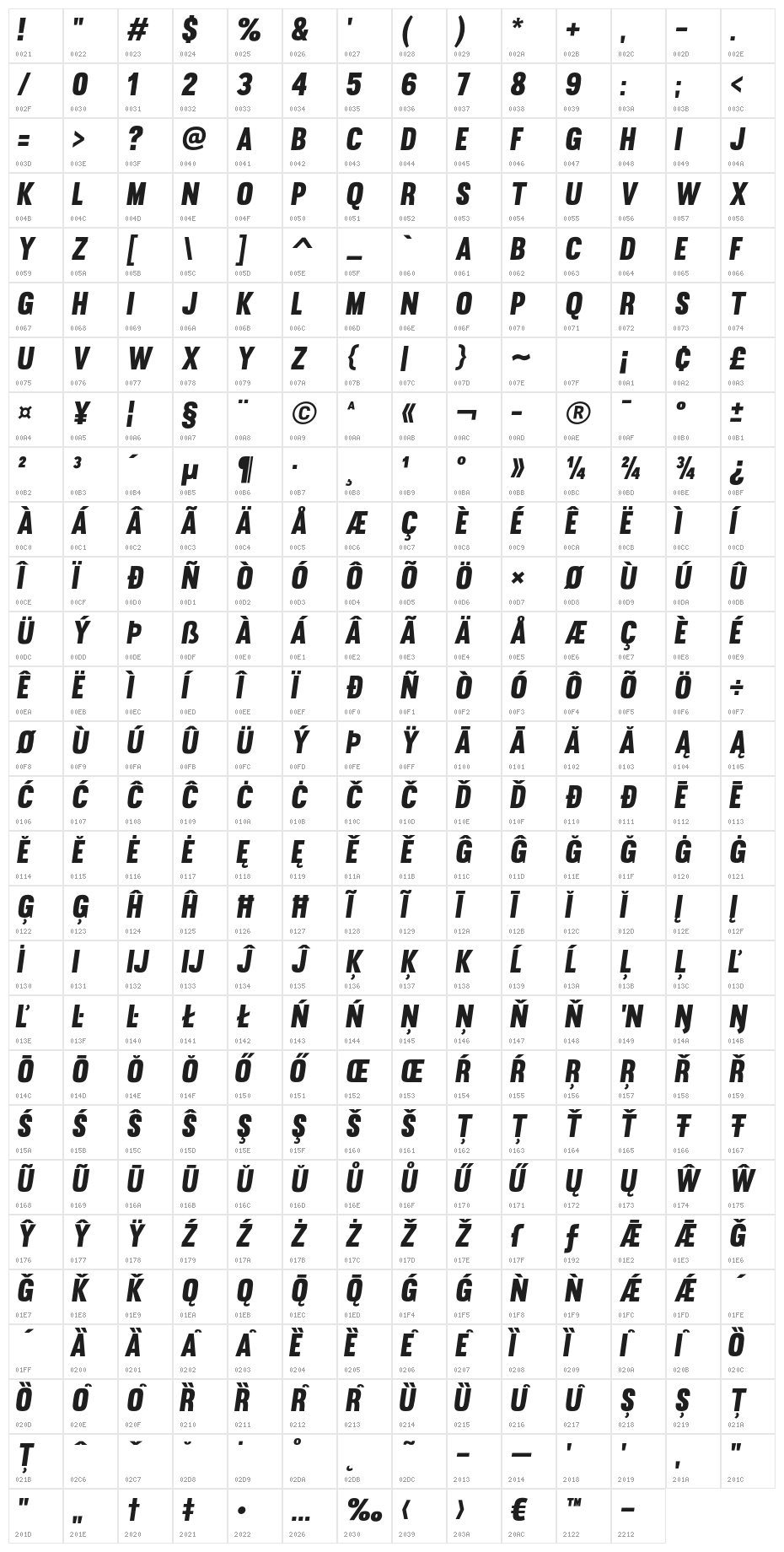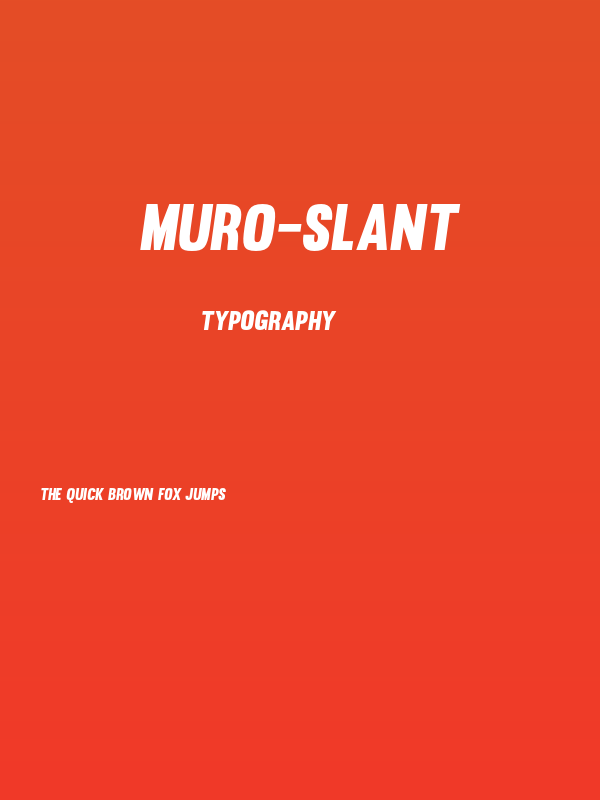
Muro-Slant Font
✎ Sans Serif
| Vorgeschlagene Projekte | Ideal for sports branding, dynamic posters, impactful headlines, and modern advertising campaigns. |